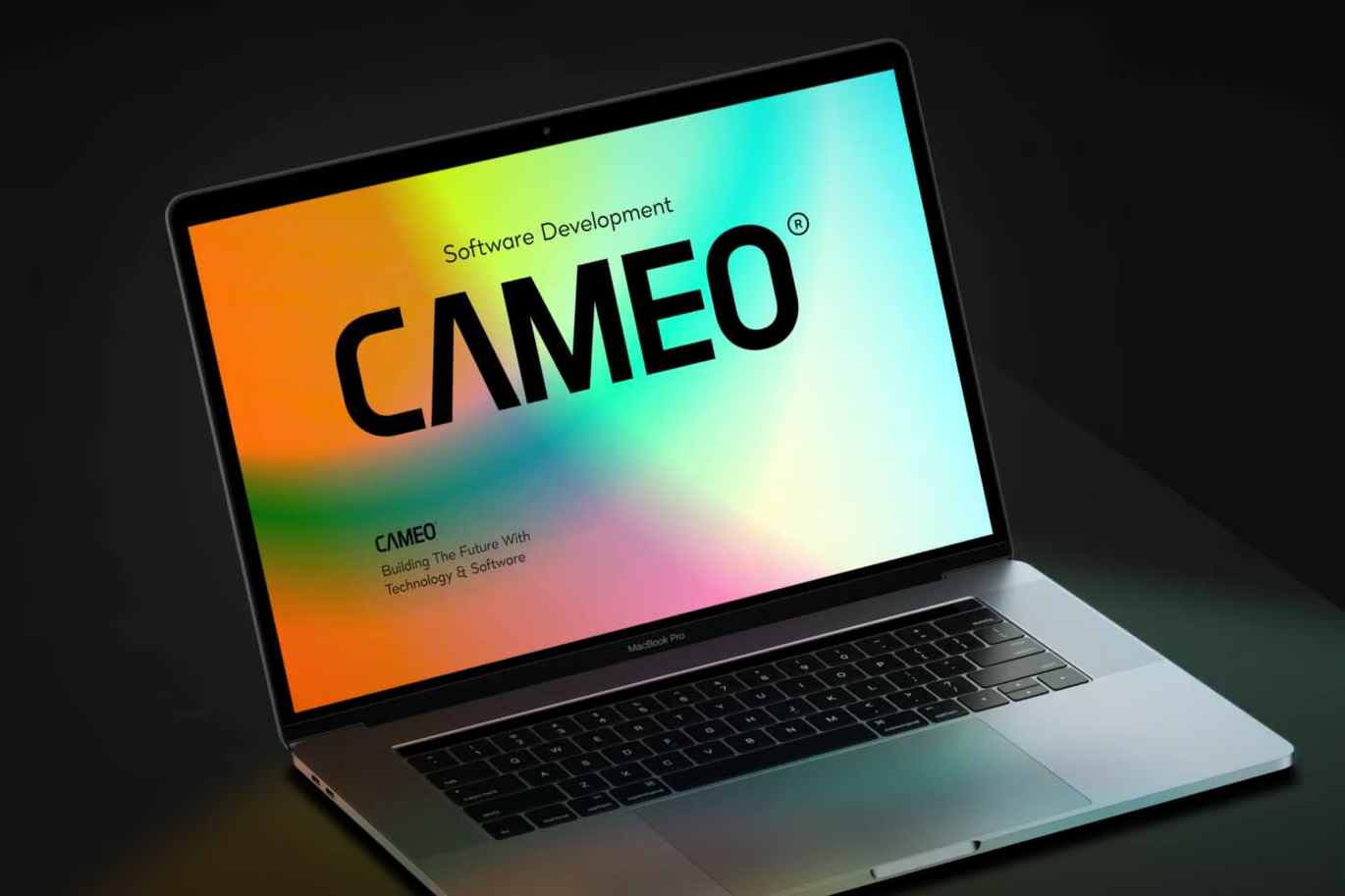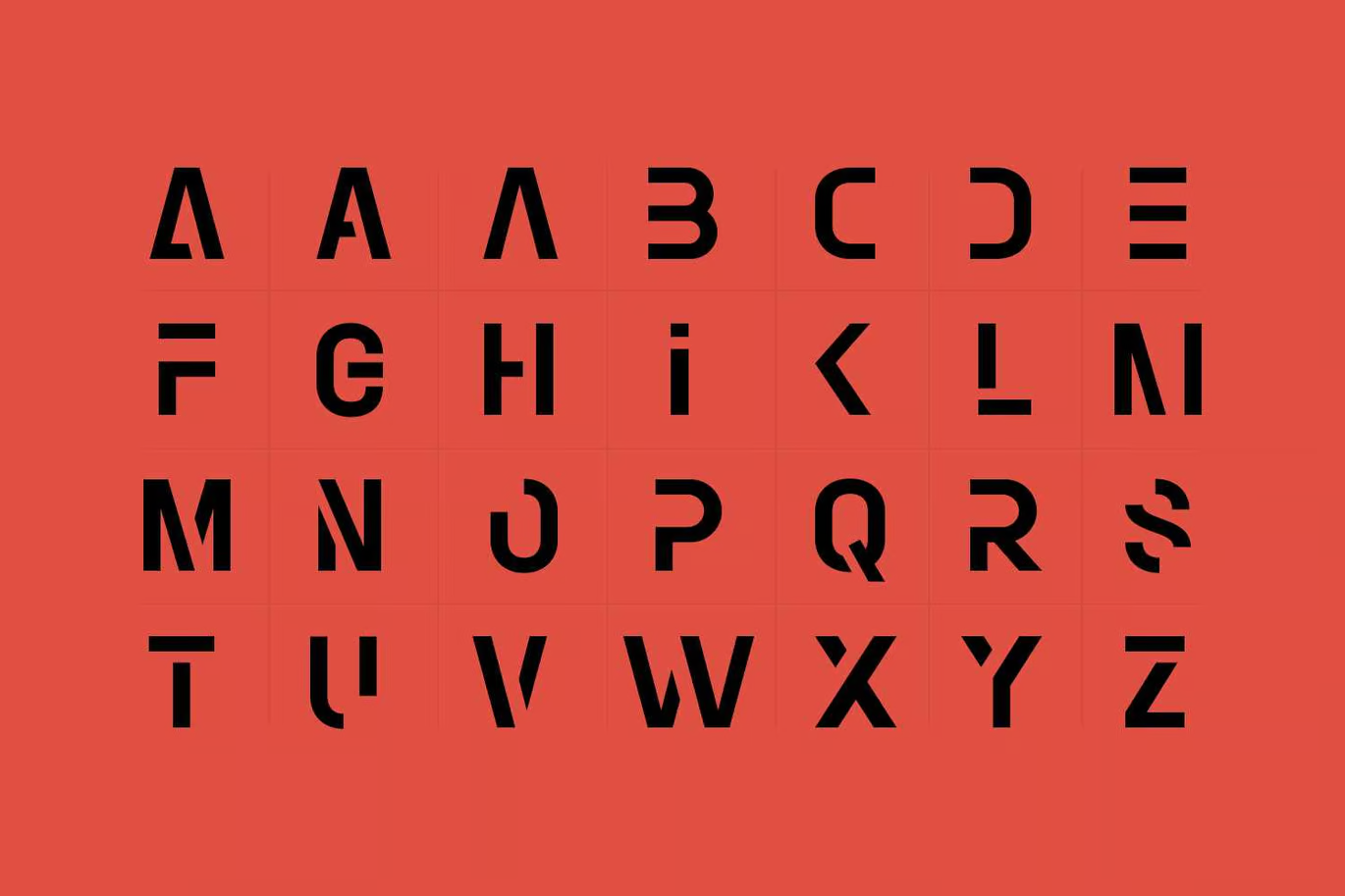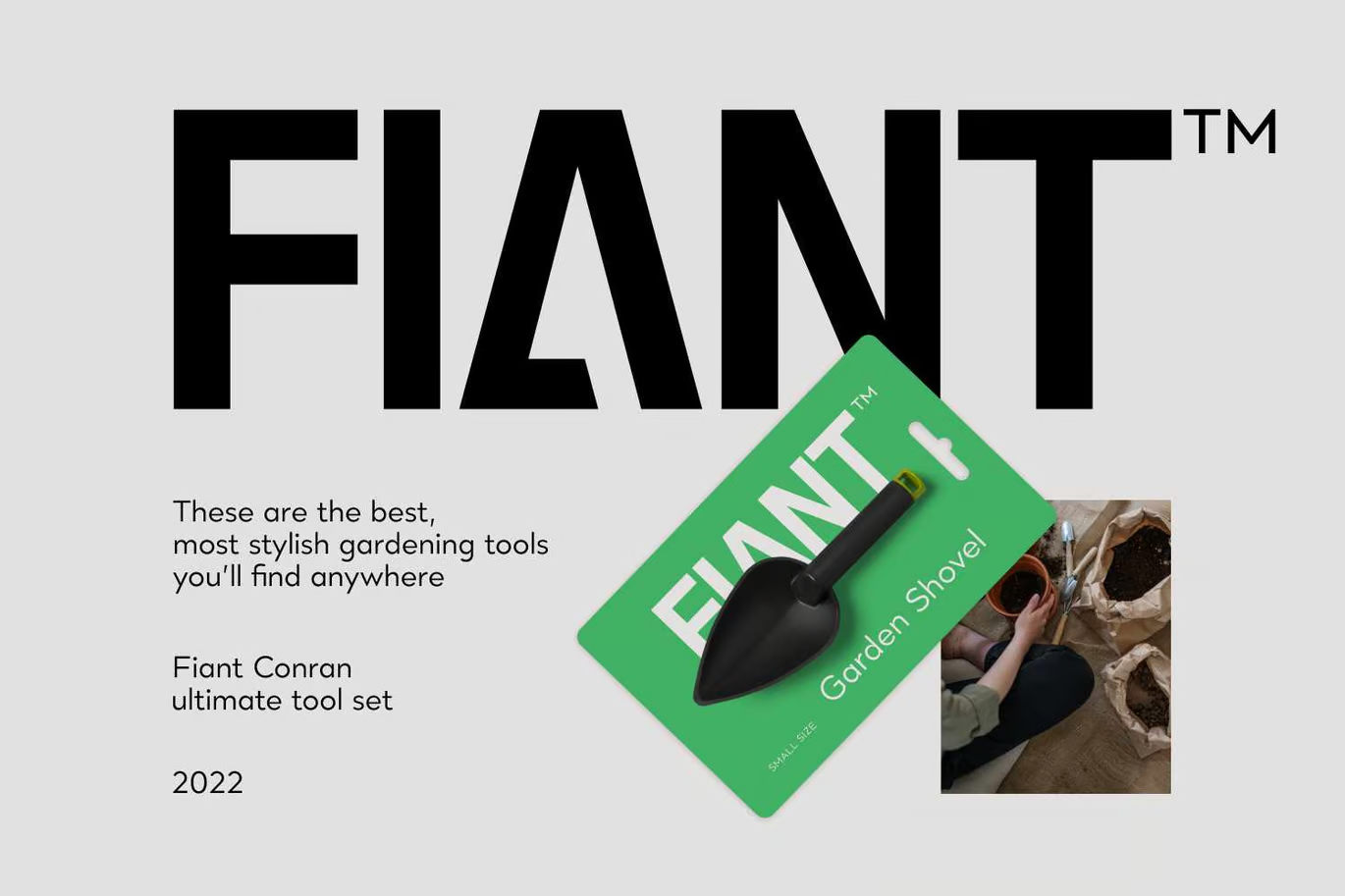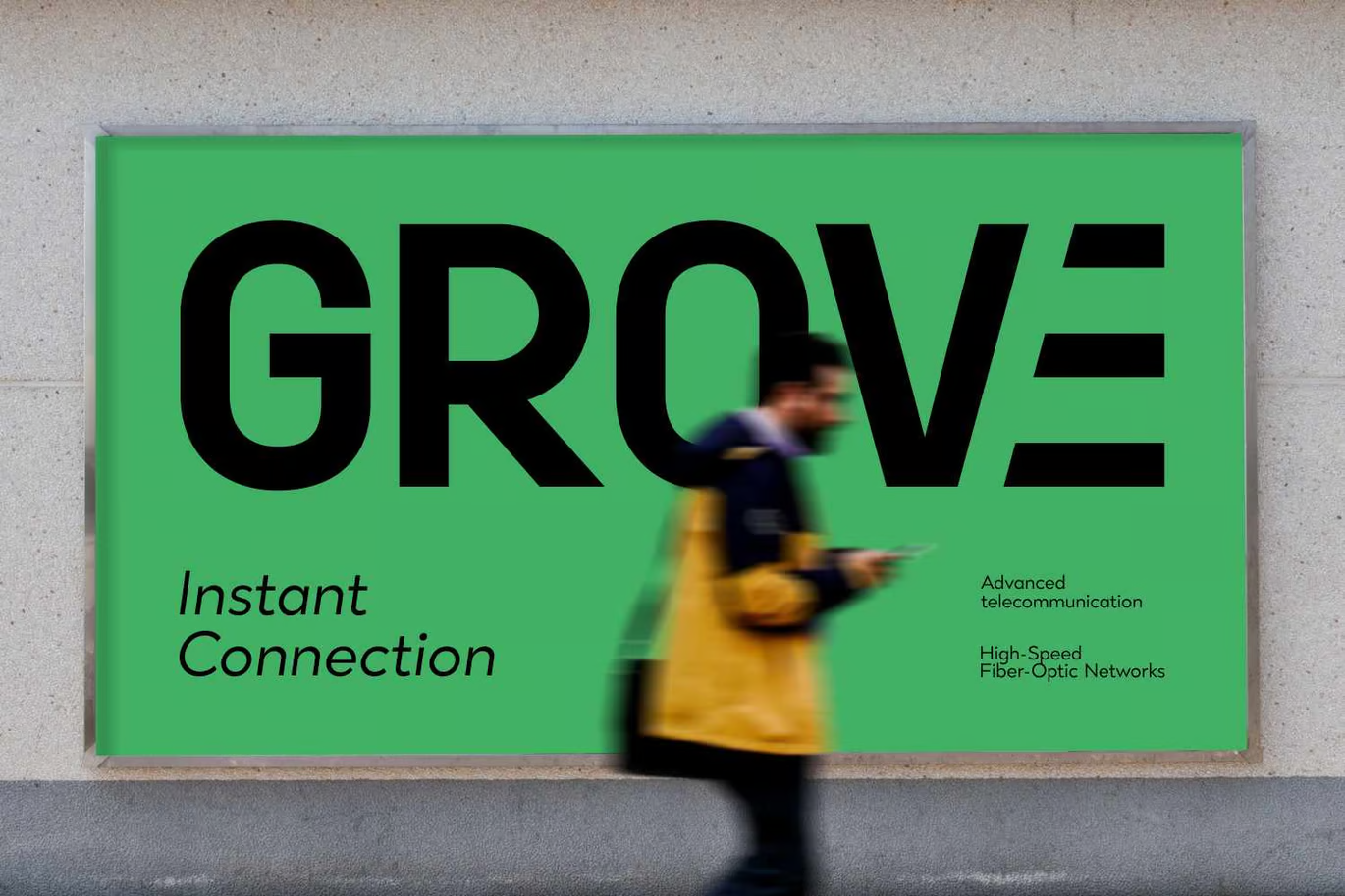
Bristol Font
Description de Bristol Font
Bristol est une police Sans Serif très flexible de logofonts, adaptée aux logos de produits, aux affiches, aux titres de titre, aux cartes de visite, aux sites Web, aux magazines, aux emballages, à la papeterie et bien plus encore. Il vous aide à concevoir votre propre type de logo car il possède une immense galerie de personnages. Bristol est livré avec des fonctionnalités OpenType qui ouvrent une bibliothèque de caractères et de ligatures supplémentaires parmi lesquels vous pouvez choisir et utiliser.